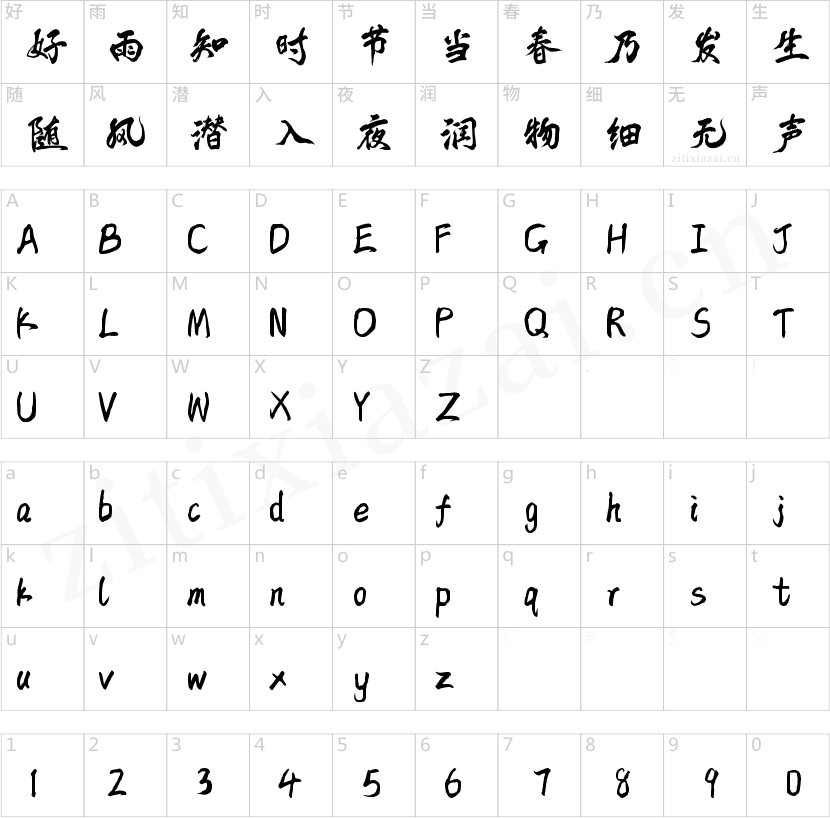
字魂凤鸣手书
字魂凤鸣手书,这款字体结构工整、笔画清晰,兼顾美观与易读性,适用于标题、正文、海报、包装、LOGO 等多种场景。字形优雅稳定,风格百搭耐看,适配日常排版与创意设计,让文字呈现更舒适、更具质感。字魂凤鸣手书一笔一画,皆是细节,以均衡的比例、流畅的线条打造舒适视觉体验,字形端正大气,风格简约现代。无论是商业设计、品牌宣传还是日常排版,都能轻松驾驭,让文字更有格调与力量。字魂凤鸣手书字体下载。